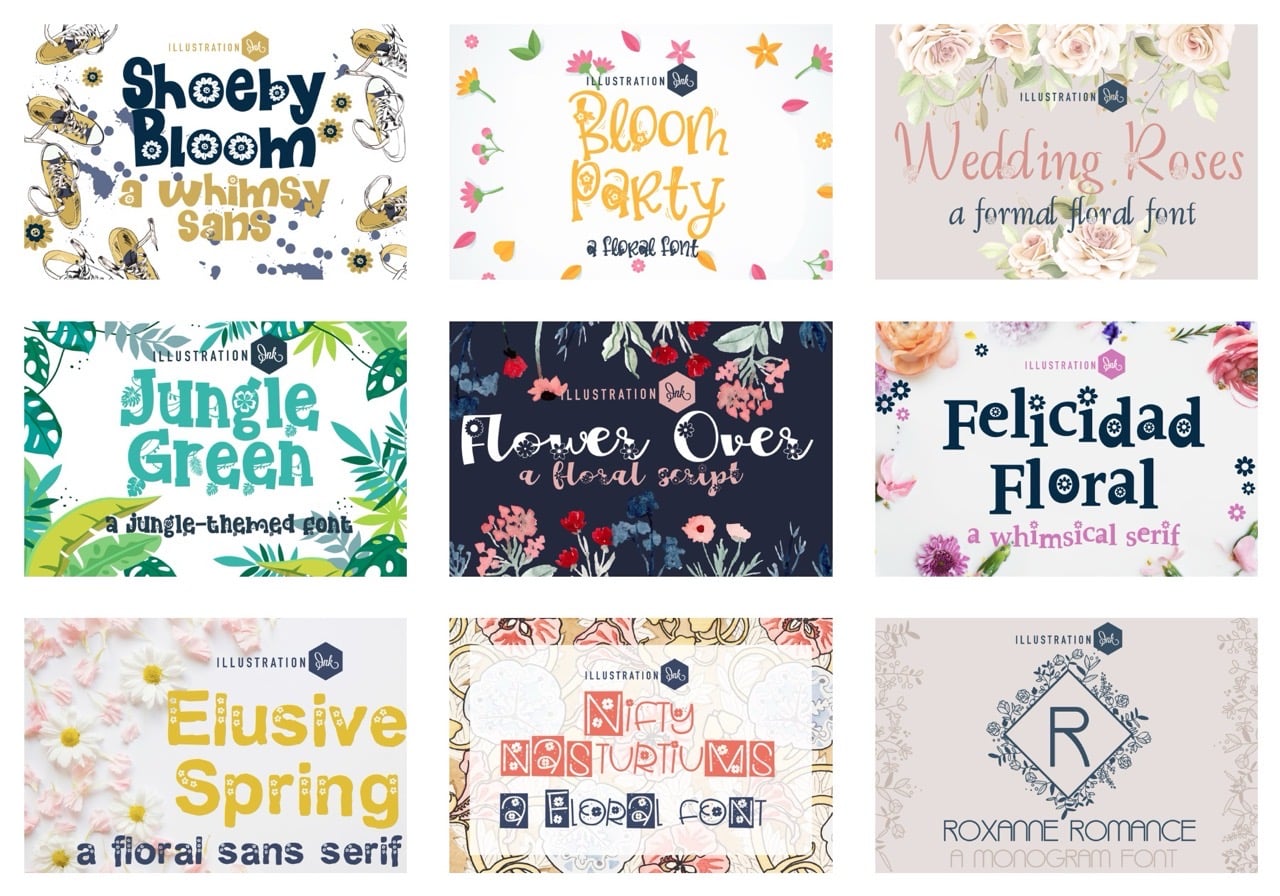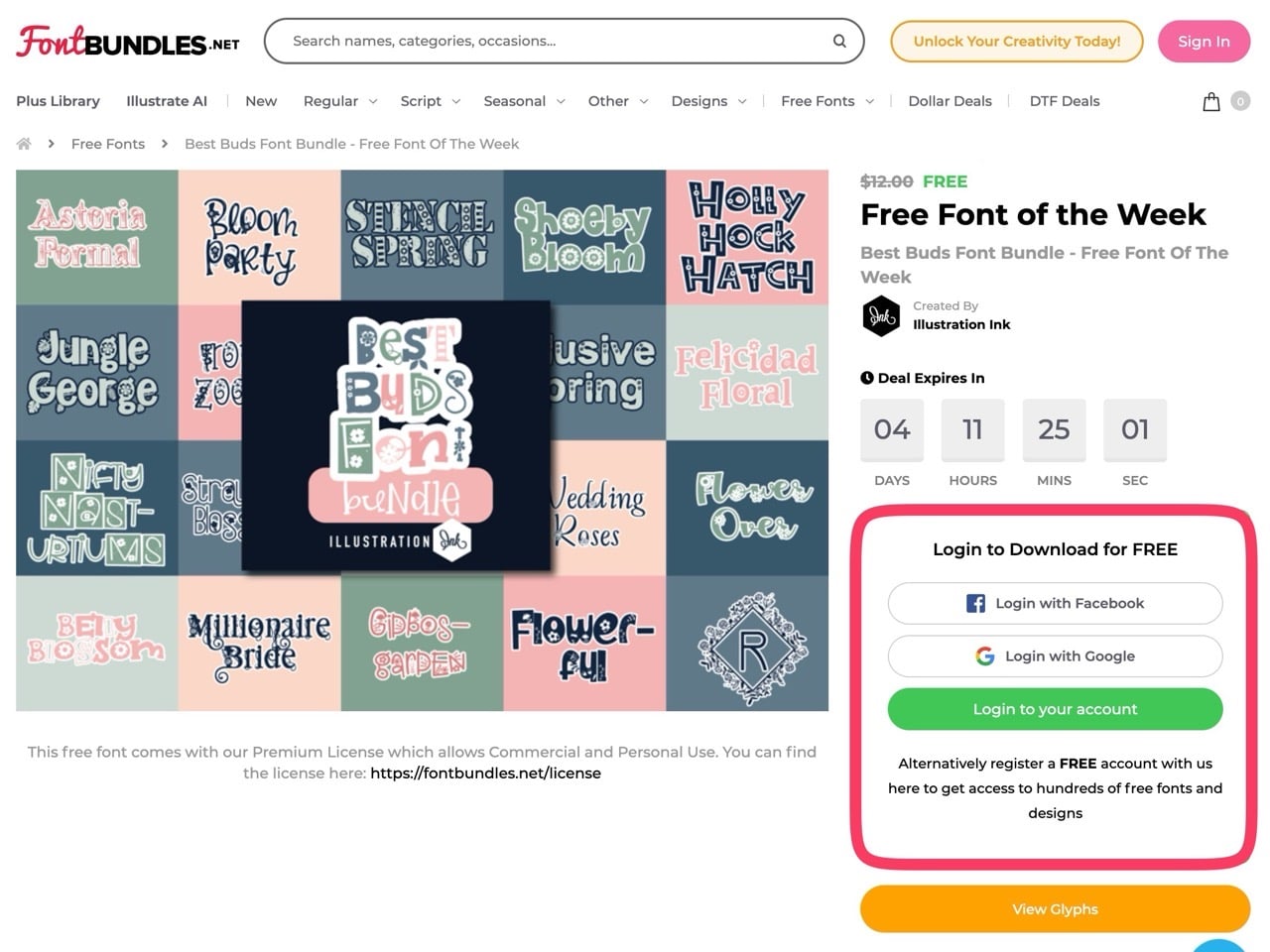
本週限免字型:充滿春天氣息的 Best Buds 系列
本週 Font Bundles 限免活動帶來「Best Buds Font Bundle」字型組合,由設計師 Illustration Ink 開發製作,這組字型的主題鮮明,充滿花卉、植物與春天的氣息,風格偏向可愛的手繪感(Doodle Style),非常適合用於海報或貼紙製作,也很符合目前的季節。